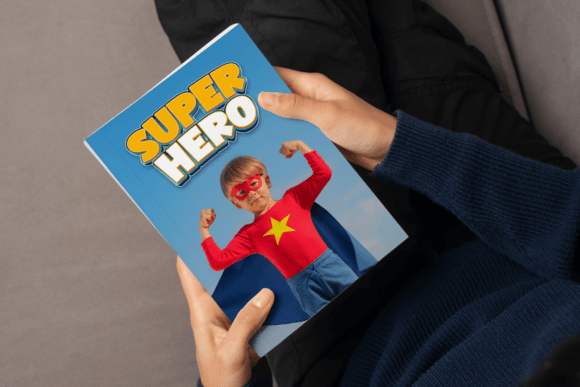
فونت Kpow Comic انگلیسی
| ⭐ توضیحات | Kpow Comic یک فونت نمایشگر ضخیم و چشم نواز است. طرح های خود را با این فونت شگفت انگیز که دارای شخصیت های سرگرم کننده و به یاد ماندنی است برجسته کنید! می توانید از آن برای پوستر، جلد کتاب، تیتر، عنوان، تی شرت و موارد دیگر استفاده کنید. |